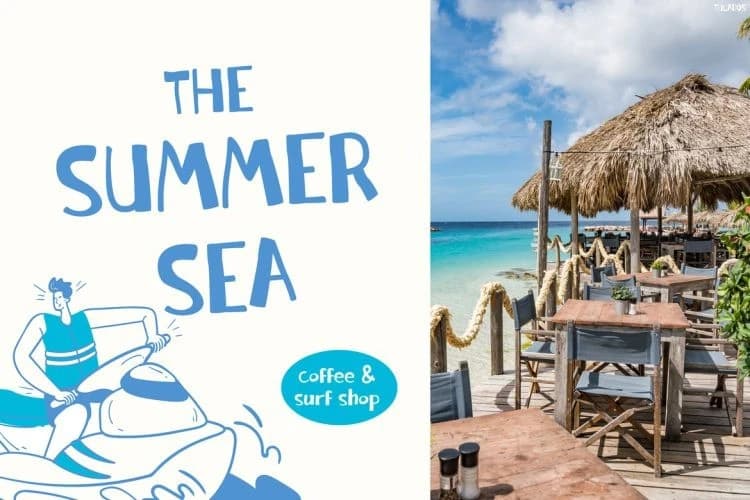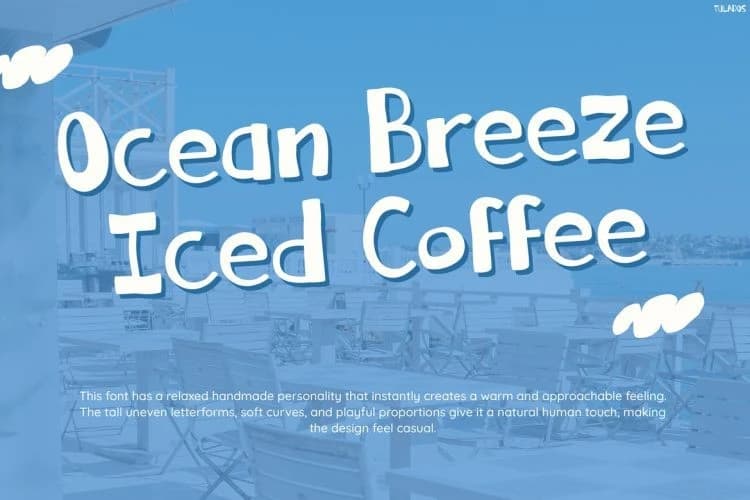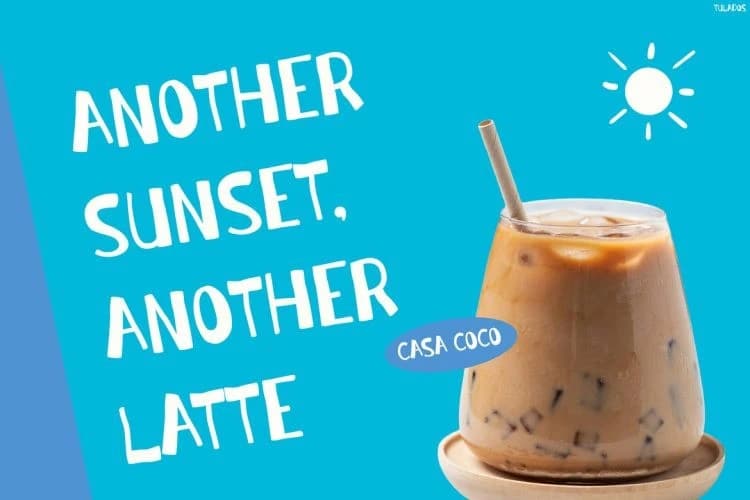
Tulados Neşeli Yazı Tipi
Tulados Playful Font, her tasarıma neşeli plaj havası, oyunbaz el yazısı biçimleri ve dinlendirici bir yaz enerjisi katar. Ayrıca, yumuşak eğriler ve sıra dışı harf biçimleri samimi bir estetik yaratır ve bu estetik hafif, eğlenceli ve anında dikkat çekici bir his verir.
Tulados Playful Font, her tasarıma neşeli plaj havası, oyuncu el yazısı biçimleri ve dinlendirici yaz mevsimi enerjisi katar. Ayrıca, yumuşak kıvrımlar ve özgün harf biçimleri, neşeli, eğlenceli ve anında dikkat çeken dostane bir estetik yaratır.
Tulados Playful